Typography, font chữ là một phần quan trọng để thêm cá tính và tạo sự chú ý cho các thiết kế từ poster, print ad, web cho đến các thiết kế động. Cùng khám phá những font chữ xu hướng và miễn phí dành cho các designer thể hiện thiết kế của mình.
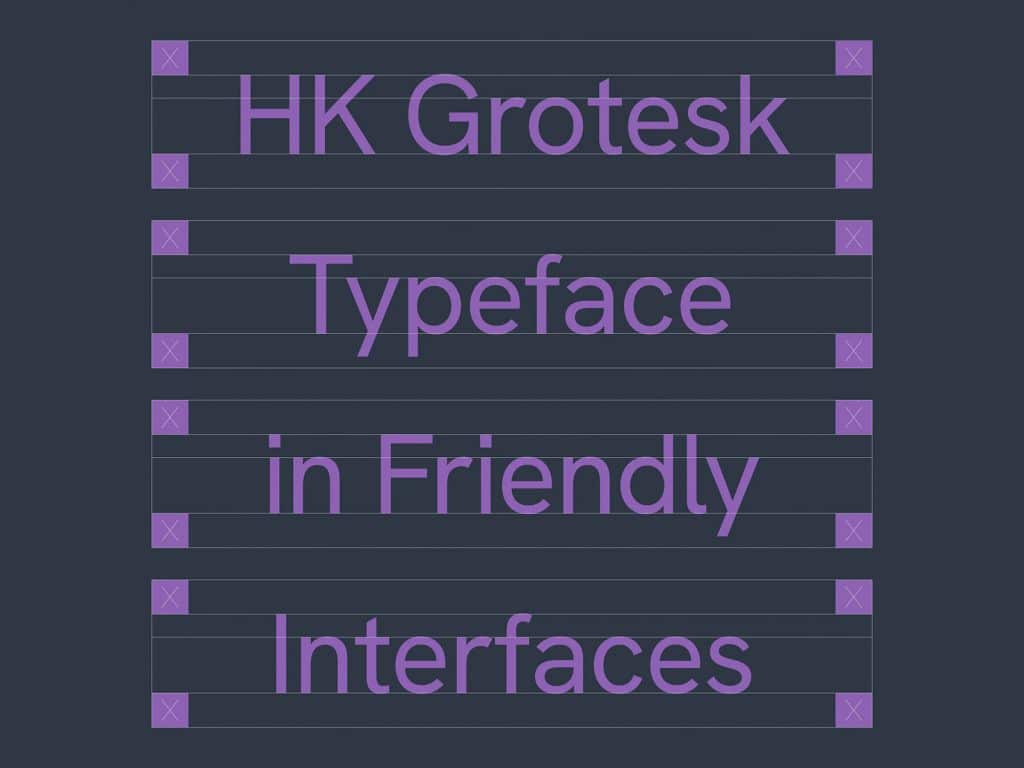
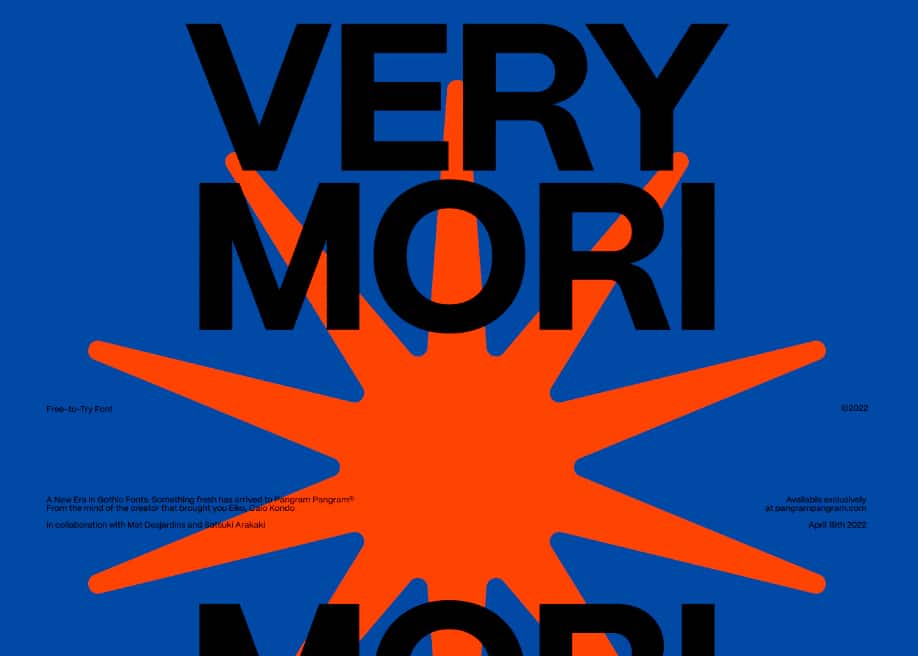
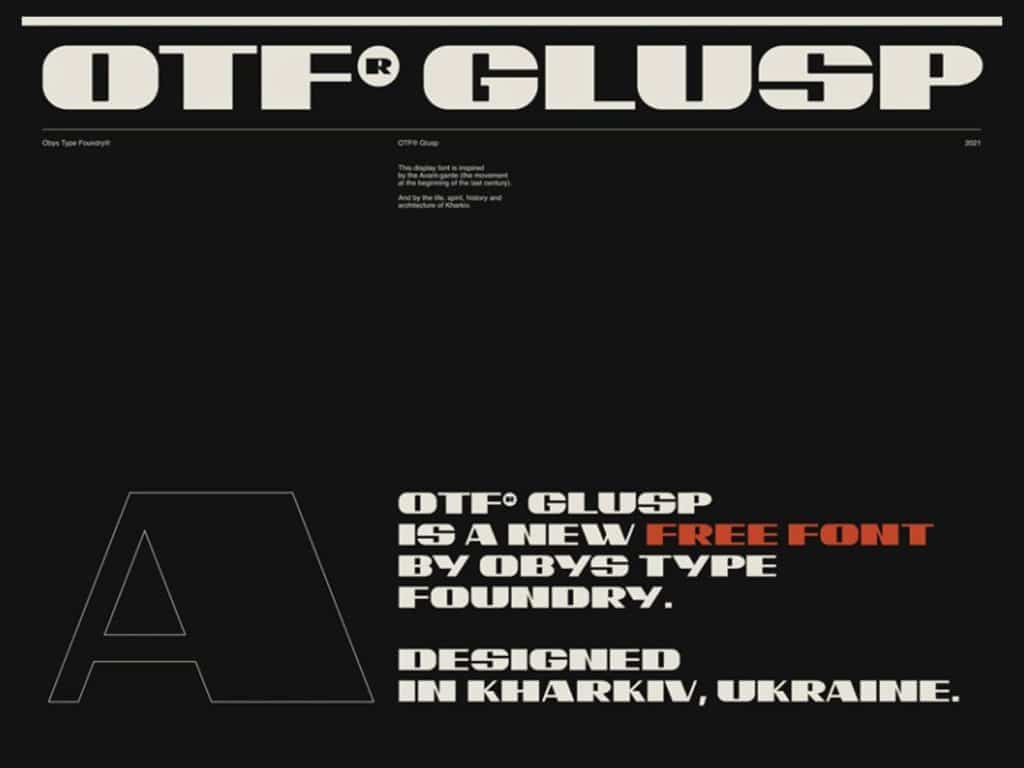
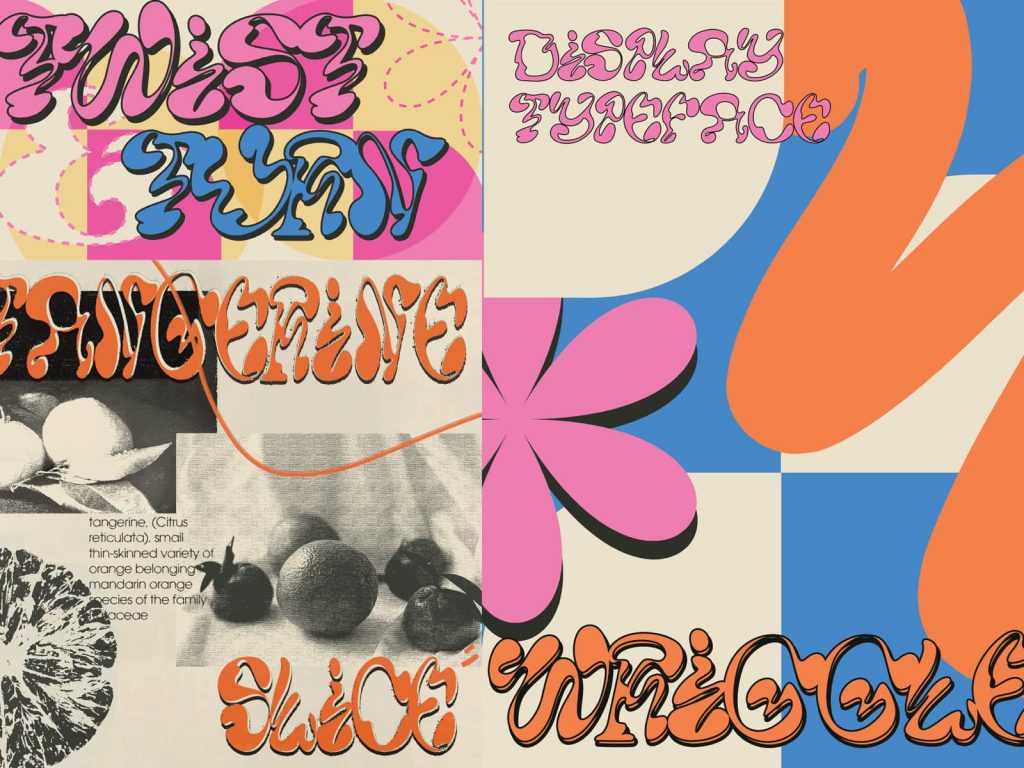
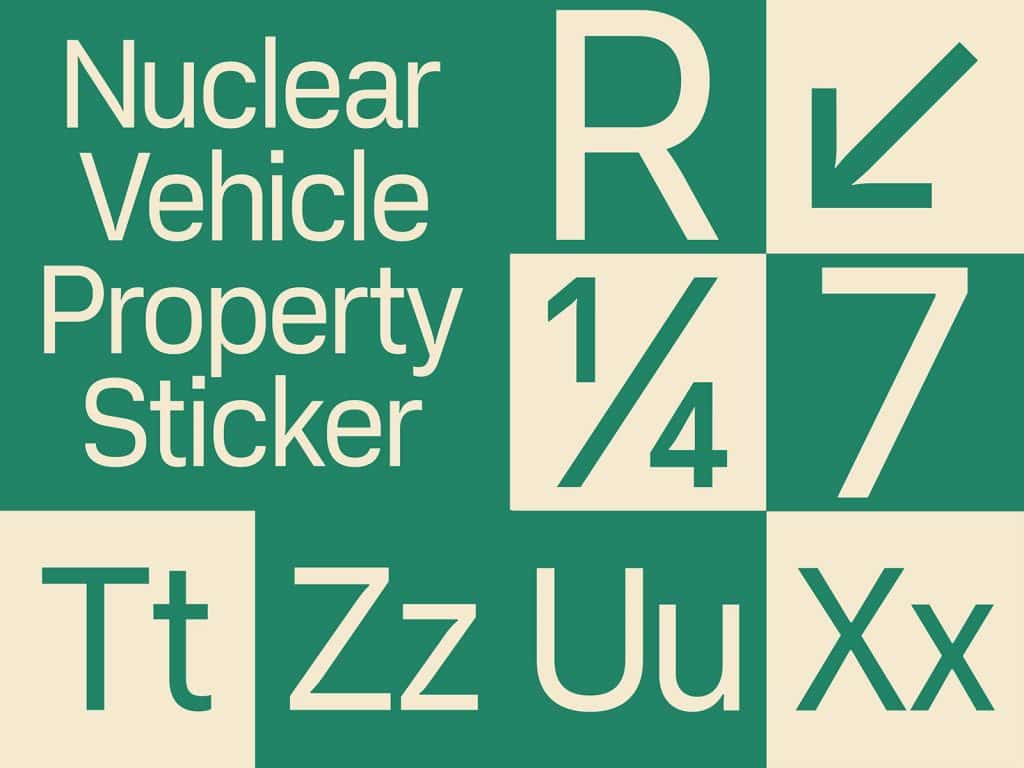
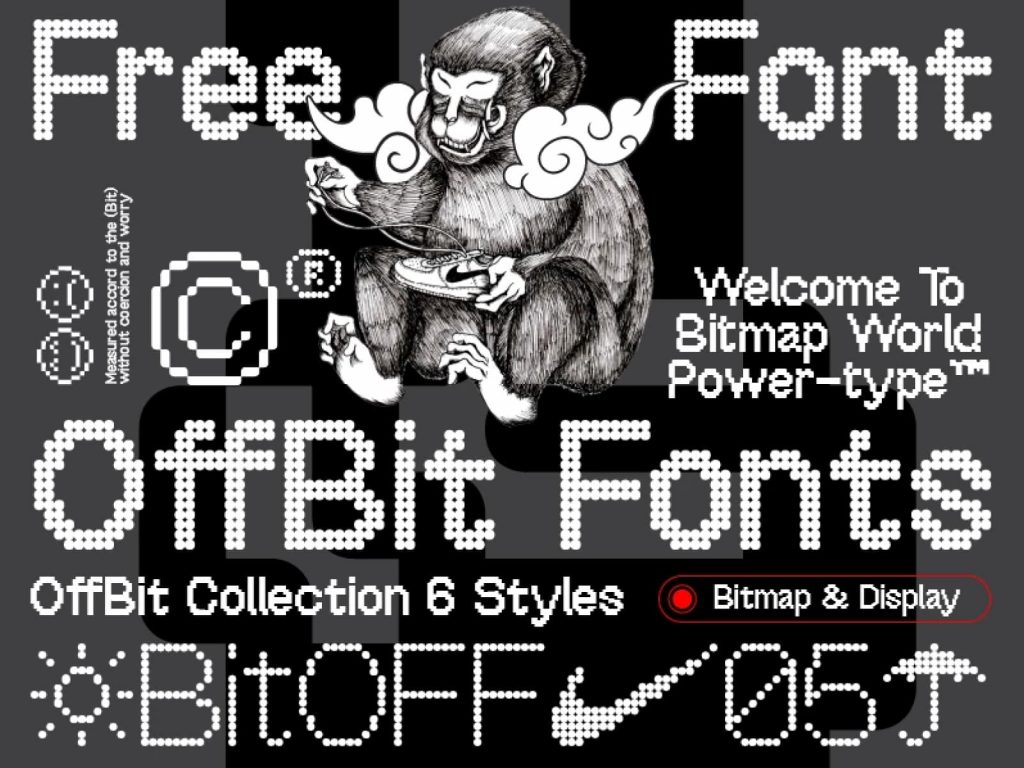
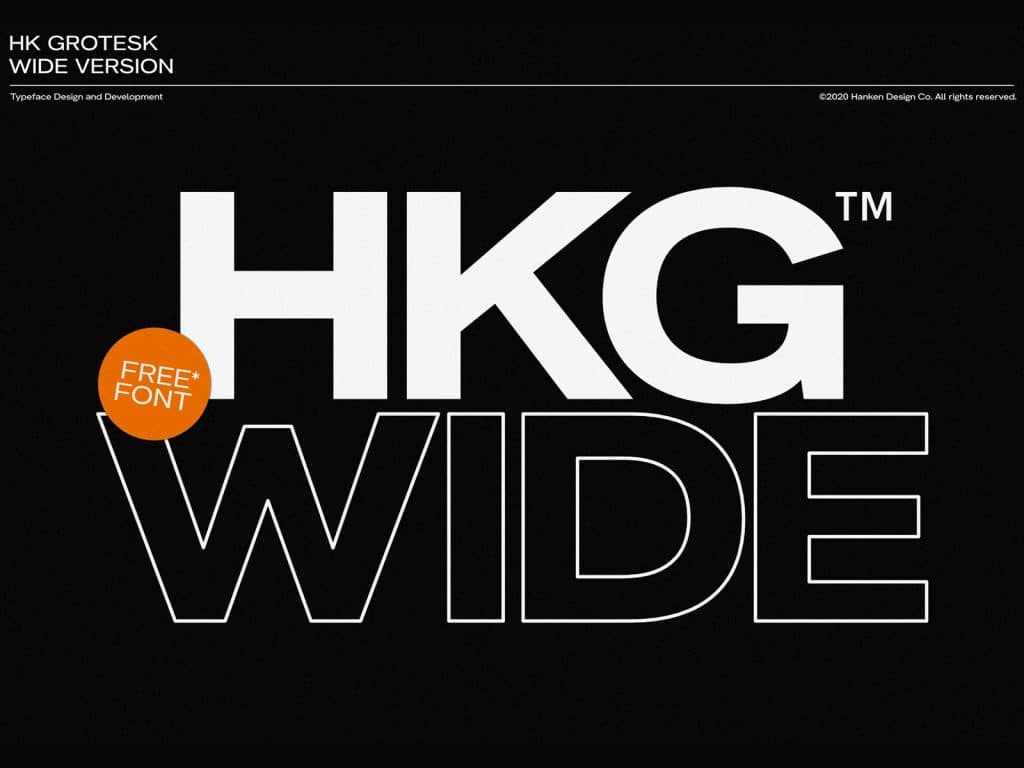
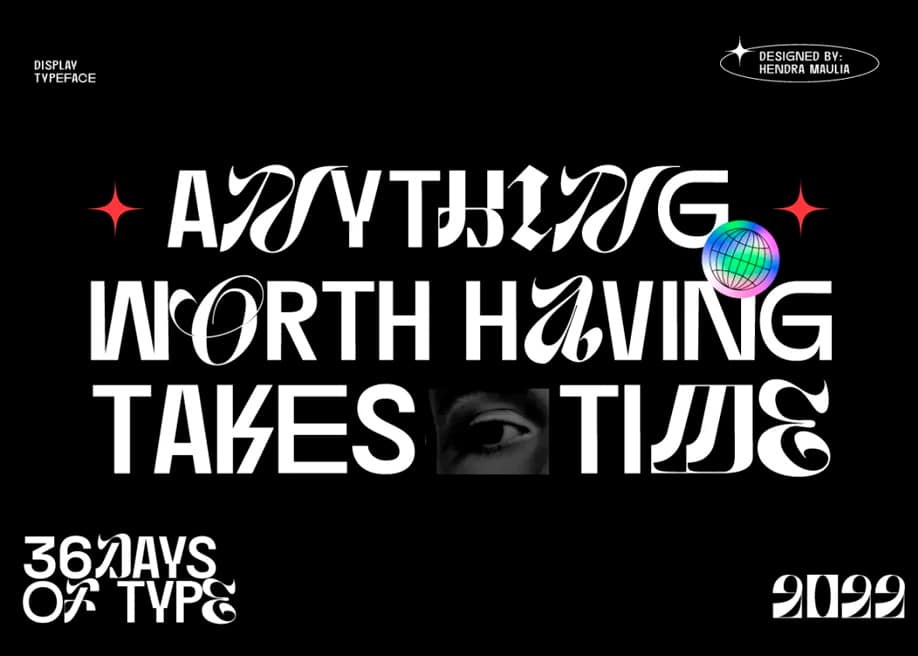
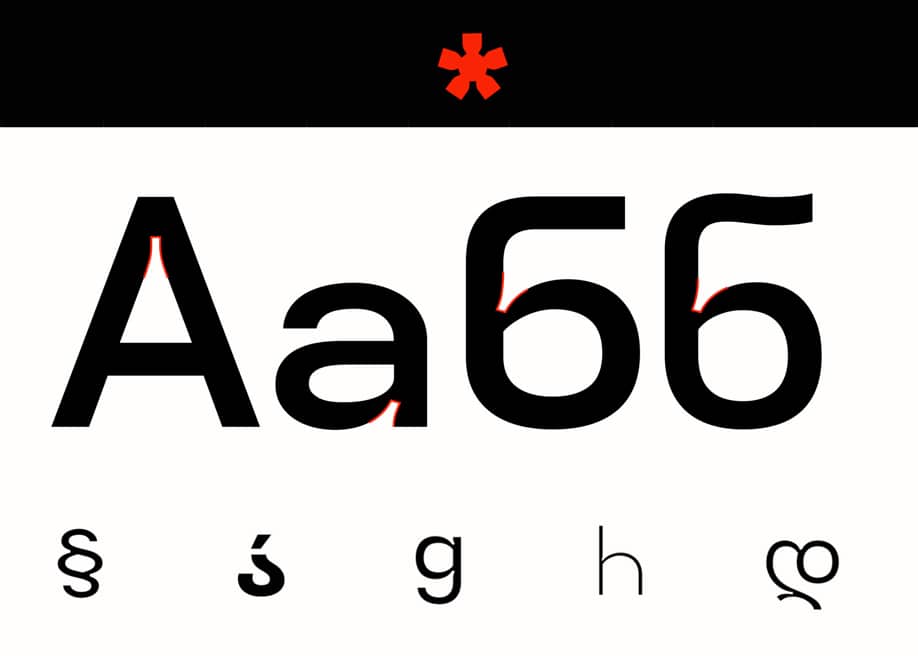
Mersad – Free Variable Typeface
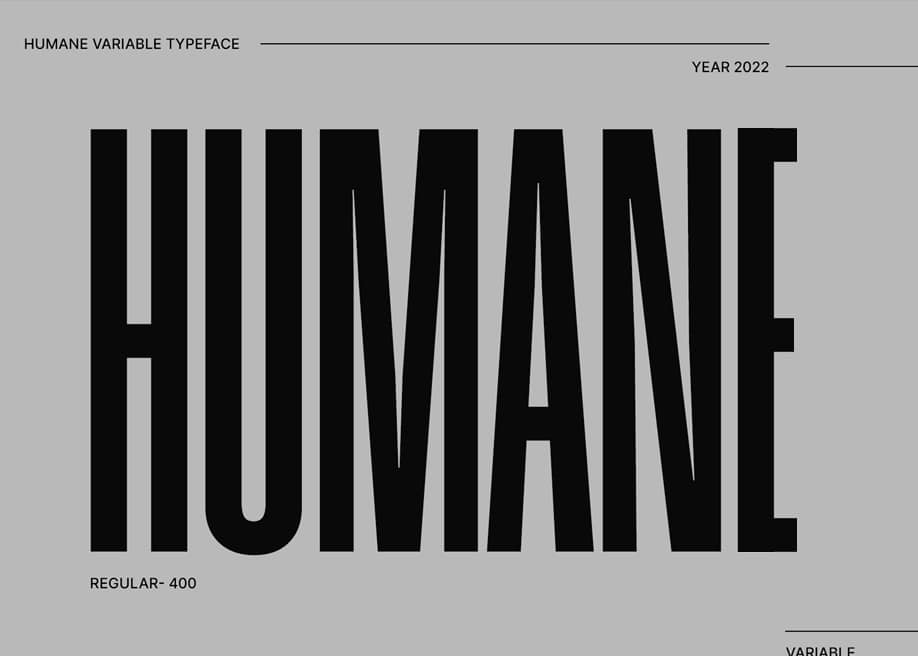
Heming a Free Variable Monotype Font
Black Sansa Thin – Free Retro Display Font
Triakis – Free Regular Weight Font
Melody Variable Font (Bản dùng thử)
Neutral Face – Sans serif free font
Avenue Mono (Bản dùng thử)
Bigilla: A display serif typeface with ligatures and alternates
Kenoky & Coffekan – Free Fonts
Creme Espana – Free calligraphy font
Resist Sans Neo-Grotesque Font
Saint Regus – Free Display Typeface
MONIQA TYPEFACE by Rajesh Rajput
Projekt Blackbird – Free Sans Serif Font
Pangram Sans Rounded – Free Font
Subjectivity – Display geometric font family
Fornite Light – Free Serif Font
Eskool – free display typeface
Bigilla display serif typeface designed by Jérémie Gauthier
Disket Mono – Display monospaced, grid based typeface
Dx Rigraf font by Dirtyline Studio
Kate typeface designed by Jérémie Gauthier
Free Faces – Free typefaces collection
Neue Metana font by Dirtyline Studio
Lincoln/MITRE retro computer font
SK-Modernist: A Geometric Avant Garde like typeface
Nafta free font by Krisjanis Mezulis
Archivo Narrow Regular – Free Font
Elanor Font by Dirtyline Studio
The Polite Type – Educational free font
Trên đây là tổng hợp các phông chữ được xem là “top 100 best free fonts” dành cho các bạn designer sử dụng cho các dự án cá nhân (đối với một số phông chữ giới hạn) hoặc thương mại của mình. Hãy tạo ra những tác phẩm đẹp của mình nhé!